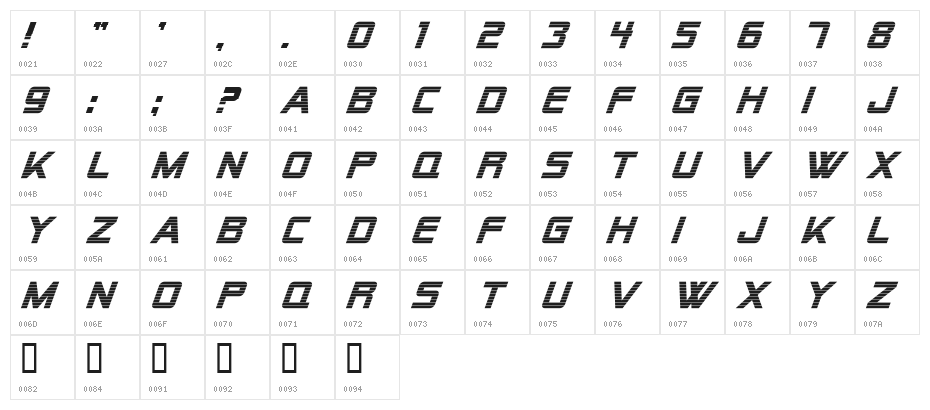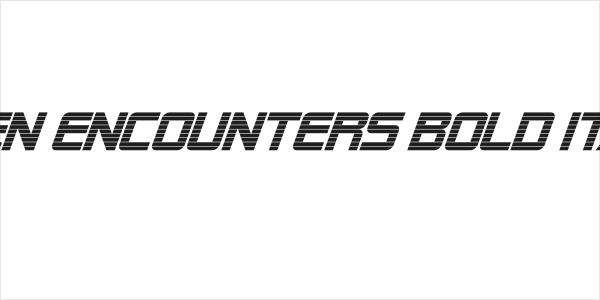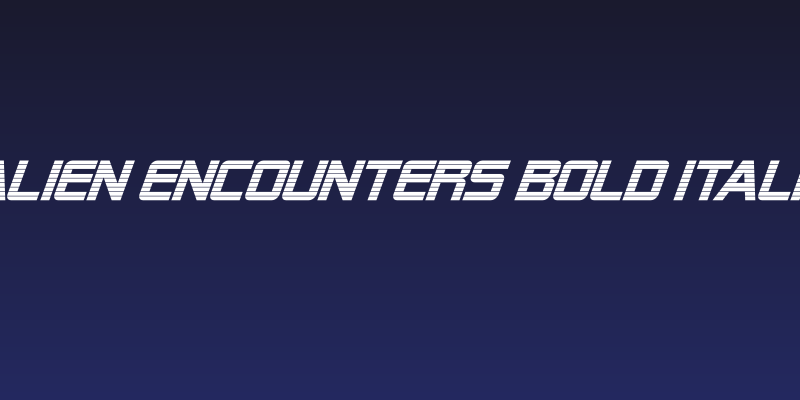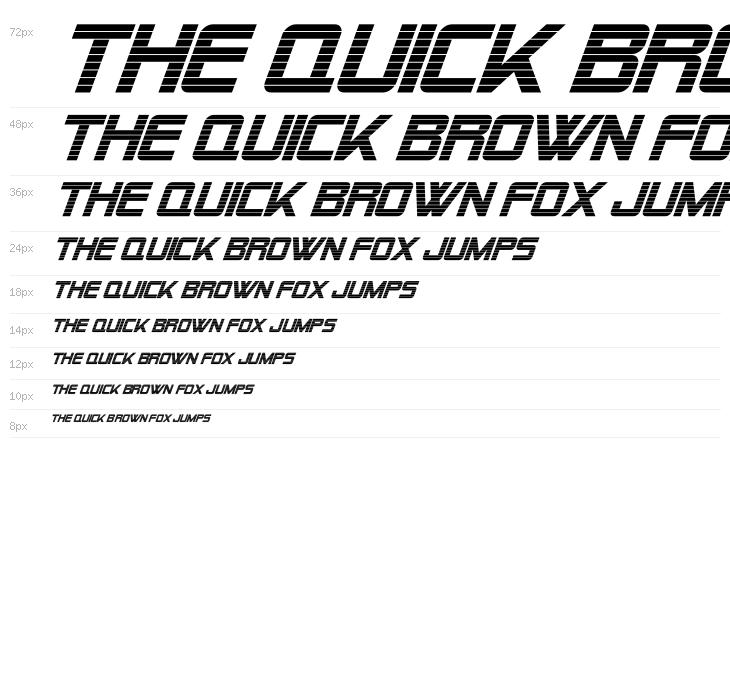
Alien Encounters Bold Italic Font
✎ Futuristic
| समग्र शैली | Futuristic |
| उपयोग का मामला | Headlines, Logos, Posters |
| सुझाए गए प्रोजेक्ट | Ideal for sci-fi themed posters, video game titles, technology branding, and futuristic event invitations. |